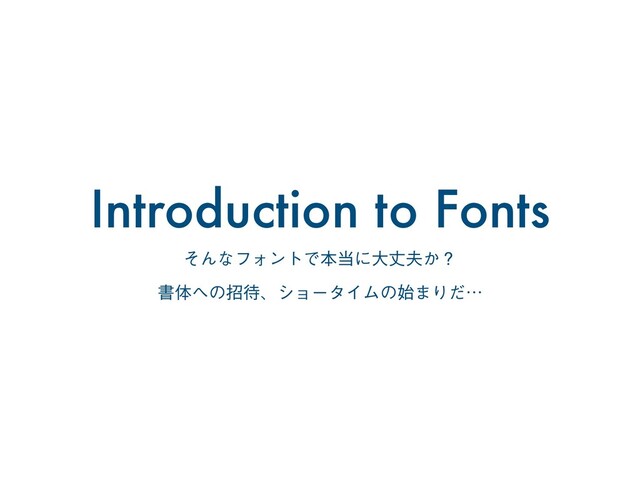
INTRODUCTION TO FONT
about font
1. ೔ຊޠॻମ w ໌ேମ ͦ૲ ʢ"05'6%ᴈϛϯ1S/ʣ w ΰγοΫମ ͦ૲ ʢ"05'தΰγοΫ###1S/ʣ w
චॻମ w σβΠϯॻମ そ草 (かづらきSP2N) ͦ૲ ʢ5"ํ؟,ʣ ԣઢʹର͠ॎઢ͕ଠ͍ ԣઢͷӈݞ΍ӈ୺ʹ΢ϩί͕͋Δ ઢͷଠ͕͞΄΅ۉҰ ΢ϩί͕શ͘ɺ͋Δ͍͸΄ͱΜͲͳ͍ චͰॻ͍ͨจࣈΛ࠶ݱͨ͠Α͏ͳॻମ खॻ͖෩ͷॻମ΍ϙοϓମͳͲ Ϋη͕ڧ͘σβΠϯੑͷߴ͍ॻମ ϕʔγοΫ ݸੑతɾบ͕ڧ͍
2. Ԥจॻମ w ηϦϑମ aA (Times New Roman) w αϯηϦϑମ aA
(Helvetica) w εΫϦϓτମ aA (zapfino) ୺ʹ૷০ʢηϦϑʣ͕͋Δ ηϦϑͷܗ͸ࡾ֯ܗɺࡉઢɺ࢛֯ܗͳͲ ηϦϑ͕ͳ͍Ԥจॻମ άϩςεΫମͱ΋ݴΘΕΔ චهମͷΑ͏ͳॻମ΍खॻ͖෩ͷॻମ ࣭ײ΋ଟछଟ༷ ϕʔγοΫ ૷০త
3. ϑΥϯτϑΝϛϦʔ Photographer, loves cycling and coffee on weekends. Photographer, loves
cycling and coffee on weekends. Photographer, loves cycling and coffee on weekends. ʢϥΠτʣ ʢϥΠτΦϒϦʔΫʣ ʢϨΪϡϥʔʣ ʢΦϒϦʔΫʣ ʢϘʔϧυʣ ʢϘʔϧυΦϒϦʔΫʣ Helvetica
4. ຊจ޲͖ͷॻମ य़͸ɺ͚͋΅ͷɻ΍͏΍ ͏ന͘ͳΓΏ͘ࢁ͗͸গ ͠໌ΓͯࢵͩͪͨΔӢͷ ࡉͨ͘ͳͼ͖ͨΔɻՆ͸ɺ ໷ɻ݄ͷࠒ͸͞ΒͳΓɻ ҋ΋ͳ΄ɻᦊͷଟ͘ඈͼ ҧͻͨΔɻ य़͸ɺ͚͋΅ͷɻ΍͏΍ ͏ന͘ͳΓΏ͘ࢁ͗͸গ
͠໌ΓͯࢵͩͪͨΔӢͷ ࡉͨ͘ͳͼ͖ͨΔɻՆ͸ɺ ໷ɻ݄ͷࠒ͸͞ΒͳΓɻ ҋ΋ͳ΄ɻᦊͷଟ͘ඈͼ ҧͻͨΔɻ ʢ"05'தΰγοΫ###1S/ʣ ʢ"05'ଠΰ#1S/ʣ ͲͪΒ͕ಡΜͰ͍ͯർΕͳ͍ʁ
5. ຊจ޲͖ͷॻମ य़͸ɺ͚͋΅ͷɻ΍͏΍ ͏ന͘ͳΓΏ͘ࢁ͗͸গ ͠໌ΓͯࢵͩͪͨΔӢͷ ࡉͨ͘ͳͼ͖ͨΔɻՆ͸ɺ ໷ɻ݄ͷࠒ͸͞ΒͳΓɻ ҋ΋ͳ΄ɻᦊͷଟ͘ඈͼ ҧͻͨΔɻ य़͸ɺ͚͋΅ͷɻ΍͏΍ ͏ന͘ͳΓΏ͘ࢁ͗͸গ
͠໌ΓͯࢵͩͪͨΔӢͷ ࡉͨ͘ͳͼ͖ͨΔɻՆ͸ɺ ໷ɻ݄ͷࠒ͸͞ΒͳΓɻ ҋ΋ͳ΄ɻᦊͷଟ͘ඈͼ ҧͻͨΔɻ ʢ"05'தΰγοΫ###1S/ʣ ʢ"05'ଠΰ#1S/ʣ ͲͪΒ͕ಡΜͰ͍ͯർΕͳ͍ʁ
6. ຊจ޲͖ͷॻମ य़͸ɺ͚͋΅ͷɻ΍͏΍ ͏ന͘ͳΓΏ͘ࢁ͗͸গ ͠໌ΓͯࢵͩͪͨΔӢͷ ࡉͨ͘ͳͼ͖ͨΔɻՆ͸ɺ ໷ɻ݄ͷࠒ͸͞ΒͳΓɻ ҋ΋ͳ΄ɻᦊͷଟ͘ඈͼ ҧͻͨΔɻ य़͸ɺ͚͋΅ͷɻ΍͏΍ ͏ന͘ͳΓΏ͘ࢁ͗͸গ
͠໌ΓͯࢵͩͪͨΔӢͷ ࡉͨ͘ͳͼ͖ͨΔɻՆ͸ɺ ໷ɻ݄ͷࠒ͸͞ΒͳΓɻ ҋ΋ͳ΄ɻᦊͷଟ͘ඈͼ ҧͻͨΔɻ ʢ"05'6%ᴈϛϯ1S/ʣ ʢ"05'தΰγοΫ###1S/ʣ ͲͪΒ͕ಡΜͰ͍ͯർΕͳ͍ʁ
7. ຊจ޲͖ͷॻମ य़͸ɺ͚͋΅ͷɻ΍͏΍ ͏ന͘ͳΓΏ͘ࢁ͗͸গ ͠໌ΓͯࢵͩͪͨΔӢͷ ࡉͨ͘ͳͼ͖ͨΔɻՆ͸ɺ ໷ɻ݄ͷࠒ͸͞ΒͳΓɻ ҋ΋ͳ΄ɻᦊͷଟ͘ඈͼ ҧͻͨΔɻ य़͸ɺ͚͋΅ͷɻ΍͏΍ ͏ന͘ͳΓΏ͘ࢁ͗͸গ
͠໌ΓͯࢵͩͪͨΔӢͷ ࡉͨ͘ͳͼ͖ͨΔɻՆ͸ɺ ໷ɻ݄ͷࠒ͸͞ΒͳΓɻ ҋ΋ͳ΄ɻᦊͷଟ͘ඈͼ ҧͻͨΔɻ ʢ"05'6%ᴈϛϯ1S/ʣ ʢ"05'தΰγοΫ###1S/ʣ ͲͪΒ͕ಡΜͰ͍ͯർΕͳ͍ʁ
8. ݟग़͠޲͖ͷॻମ य़͸ɺ͚͋΅ͷɻ΍͏΍͏ന͘ ͳΓΏ͘ࢁ͗͸গ͠໌Γͯࢵͩ ͪͨΔӢͷࡉͨ͘ͳͼ͖ͨΔɻ Ն͸ɺ໷ɻ݄ͷࠒ͸͞ΒͳΓɻ ҋ΋ͳ΄ɻᦊͷଟ͘ඈͼҧͻͨ Δɻ ʢ"05'6%ᴈϛϯ1S/ʣ य़͸͚͋΅ͷ य़͸ɺ͚͋΅ͷɻ΍͏΍͏ന͘
ͳΓΏ͘ࢁ͗͸গ͠໌Γͯࢵͩ ͪͨΔӢͷࡉͨ͘ͳͼ͖ͨΔɻ Ն͸ɺ໷ɻ݄ͷࠒ͸͞ΒͳΓɻ ҋ΋ͳ΄ɻᦊͷଟ͘ඈͼҧͻͨ Δɻ ʢ"05'6%ᴈϛϯ1S/ʣ य़͸͚͋΅ͷ ͲͪΒ͕ࢹೝੑ͕ߴ͍ʁ
9. ݟग़͠޲͖ͷॻମ य़͸ɺ͚͋΅ͷɻ΍͏΍͏ന͘ ͳΓΏ͘ࢁ͗͸গ͠໌Γͯࢵͩ ͪͨΔӢͷࡉͨ͘ͳͼ͖ͨΔɻ Ն͸ɺ໷ɻ݄ͷࠒ͸͞ΒͳΓɻ ҋ΋ͳ΄ɻᦊͷଟ͘ඈͼҧͻͨ Δɻ ʢ"05'6%ᴈϛϯ1S/ʣ य़͸͚͋΅ͷ य़͸ɺ͚͋΅ͷɻ΍͏΍͏ന͘
ͳΓΏ͘ࢁ͗͸গ͠໌Γͯࢵͩ ͪͨΔӢͷࡉͨ͘ͳͼ͖ͨΔɻ Ն͸ɺ໷ɻ݄ͷࠒ͸͞ΒͳΓɻ ҋ΋ͳ΄ɻᦊͷଟ͘ඈͼҧͻͨ Δɻ ʢ"05'6%ᴈϛϯ1S/ʣ य़͸͚͋΅ͷ ͲͪΒ͕ςʔϚʹ߹͍ͬͯΔʁ
10. ݟग़͠޲͖ͷॻମ य़͸ɺ͚͋΅ͷɻ΍͏΍͏ന͘ ͳΓΏ͘ࢁ͗͸গ͠໌Γͯࢵͩ ͪͨΔӢͷࡉͨ͘ͳͼ͖ͨΔɻ Ն͸ɺ໷ɻ݄ͷࠒ͸͞ΒͳΓɻ ҋ΋ͳ΄ɻᦊͷଟ͘ඈͼҧͻͨ Δɻ ʢ"05'6%ᴈϛϯ1S/ʣ य़͸͚͋΅ͷ य़͸ɺ͚͋΅ͷɻ΍͏΍͏ന͘
ͳΓΏ͘ࢁ͗͸গ͠໌Γͯࢵͩ ͪͨΔӢͷࡉͨ͘ͳͼ͖ͨΔɻ Ն͸ɺ໷ɻ݄ͷࠒ͸͞ΒͳΓɻ ҋ΋ͳ΄ɻᦊͷଟ͘ඈͼҧͻͨ Δɻ ʢ"05'6%ᴈϛϯ1S/ʣ य़͸͚͋΅ͷ ͲͪΒ͕ςʔϚʹ߹͍ͬͯΔʁ
11. ʢ"05'6%ᴈϛϯ1S/ʣ य़͸ɺ͚͋΅ͷɻ΍͏΍͏ന͘ͳΓΏ ͘ࢁ͗͸গ͠໌ΓͯࢵͩͪͨΔӢͷࡉ ͨ͘ͳͼ͖ͨΔɻՆ͸ɺ໷ɻ݄ͷࠒ͸ ͞ΒͳΓɻҋ΋ͳ΄ɻᦊͷଟ͘ඈͼҧ ͻͨΔɻ ʢ"05'6%ᴈϛϯ1S/ʣ य़͸͚͋΅ͷ λΠτϧ޲͖ͷॻମ 枕草⼦
ປ૲ࢠ ͲͪΒʹ໨Λऒ͔ΕΔʁ य़͸ɺ͚͋΅ͷɻ΍͏΍͏ന͘ͳΓΏ ͘ࢁ͗͸গ͠໌ΓͯࢵͩͪͨΔӢͷࡉ ͨ͘ͳͼ͖ͨΔɻՆ͸ɺ໷ɻ݄ͷࠒ͸ ͞ΒͳΓɻҋ΋ͳ΄ɻᦊͷଟ͘ඈͼҧ ͻͨΔɻ ʢ"05'6%ᴈϛϯ1S/ʣ य़͸͚͋΅ͷ
12. ʢ"05'6%ᴈϛϯ1S/ʣ य़͸ɺ͚͋΅ͷɻ΍͏΍͏ന͘ͳΓΏ ͘ࢁ͗͸গ͠໌ΓͯࢵͩͪͨΔӢͷࡉ ͨ͘ͳͼ͖ͨΔɻՆ͸ɺ໷ɻ݄ͷࠒ͸ ͞ΒͳΓɻҋ΋ͳ΄ɻᦊͷଟ͘ඈͼҧ ͻͨΔɻ ʢ"05'6%ᴈϛϯ1S/ʣ य़͸͚͋΅ͷ λΠτϧ޲͖ͷॻମ 枕草⼦
ປ૲ࢠ ͲͪΒʹ໨Λऒ͔ΕΔʁ य़͸ɺ͚͋΅ͷɻ΍͏΍͏ന͘ͳΓΏ ͘ࢁ͗͸গ͠໌ΓͯࢵͩͪͨΔӢͷࡉ ͨ͘ͳͼ͖ͨΔɻՆ͸ɺ໷ɻ݄ͷࠒ͸ ͞ΒͳΓɻҋ΋ͳ΄ɻᦊͷଟ͘ඈͼҧ ͻͨΔɻ ʢ"05'6%ᴈϛϯ1S/ʣ य़͸͚͋΅ͷ